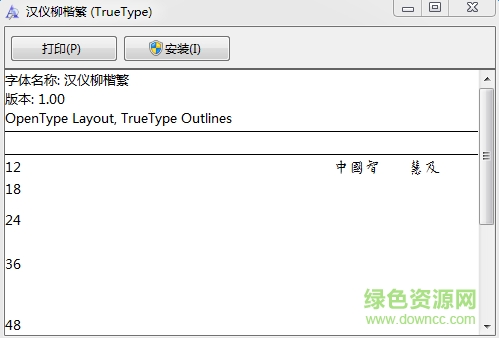
軟件介紹 軟件標(biāo)簽: 漢儀字體 字體 漢儀柳楷繁體是漢儀字體中比較實(shí)用的一款繁體字,這款字體寫出來的字瀟灑、美觀,而且很耐看,所以小編為大家推薦了這款字體,有需要的朋友可以來綠色資源網(wǎng)下載。安裝說明:第一種1.下載字體并解壓縮;2.開始中打開控制面板;3.在控制面板中打開字體文件夾;4.把下載的字體復(fù)制到此文件夾下;5.文字添加完成第二種1.下載字體并解壓縮;2.把文件根目錄下的字體壓縮包解壓縮;3.把文件根目錄下的安裝字體.bat放到含有字體文件的文件夾中,雙擊安裝字體.bat軟件;4.文字添加完成 本字體如果商用,請聯(lián)系漢儀字體官方獲得授權(quán)。 軟件截圖 上一張下一張(1 / 1) 安裝詳細(xì)截圖 其他版本下載 標(biāo)題 大小 更新日期 下載 下載地址 電腦版 漢儀柳楷繁 點(diǎn)擊報(bào)錯(cuò) 軟件無法下載或下載后無法使用,請點(diǎn)擊報(bào)錯(cuò),謝謝! 關(guān)閉報(bào)錯(cuò)反饋 請描述您所遇到的錯(cuò)誤,我們將盡快予以修正,謝謝! *必填項(xiàng),請輸入內(nèi)容 本類最新 漢儀孟瑞體ttf v1.0 官方版 漢儀字庫免費(fèi) 132款 阿里巴巴普惠字體 官方ttf版 漢儀字體打包大全 for Mac 蘋果電腦版_ 共131款字體 漢儀純愛情書拼音體 ttf版 漢儀北魏寫經(jīng)w字體 免費(fèi)版 相關(guān)文章 Photoshop字體安裝使用方法和技巧 如何解決“無法新增字體”問題 Win 7系統(tǒng)安裝字體方法 網(wǎng)頁字體大小設(shè)置方法 怎么改網(wǎng)頁字體大小 在Linux系統(tǒng)中安裝字體的幾種方法 windows7字體顯示問題:打開某些程序的時(shí)候顯示的是亂碼 用戶評論 熱門評論 最新評論 發(fā)表評論 查看所有評論(0) 昵稱: 請不要評論無意義或臟話,我們所有評論會有人工審核. 字?jǐn)?shù): 0/500 (您的評論需要經(jīng)過審核才能顯示)